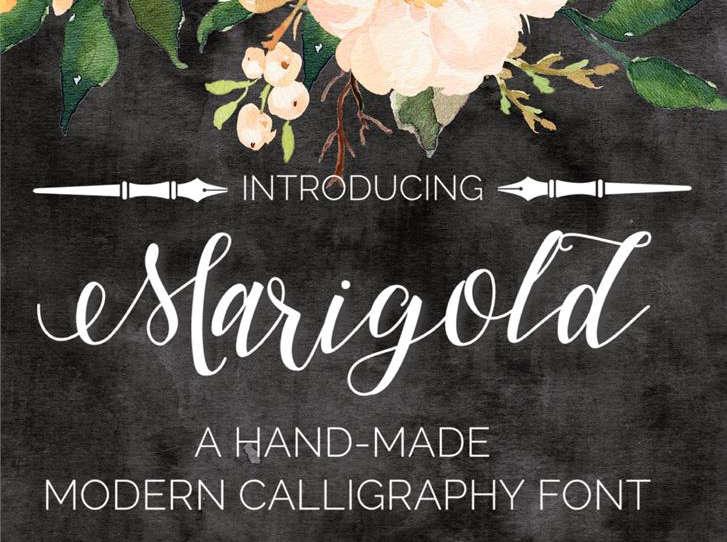
Marigold Font – Fonte Grátis
Marigold Font
A font Marigold é uma criação meticulosa da designer SarahTaylorDesigns que busca capturar a essência autêntica e vibrante do estilo à mão de letramento moderno. Afinal de contas, o objetivo era criar uma fonte que fosse quase idêntica às letras escritas à mão do próprio criador. Esta font faz do letramento moderno de arte manual algo acessível para todos os tipos de projetos. É perfeita para aniversários e casamentos, cartões, design web, logotipos, assinaturas, estaçãoaria e qualquer outro projeto que você possa imaginar. Marigold é a sua fonte ideal para dar vida à suas criações de arte manual com um toque autêntico.